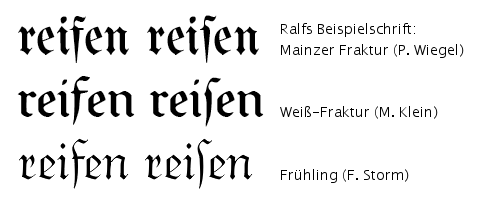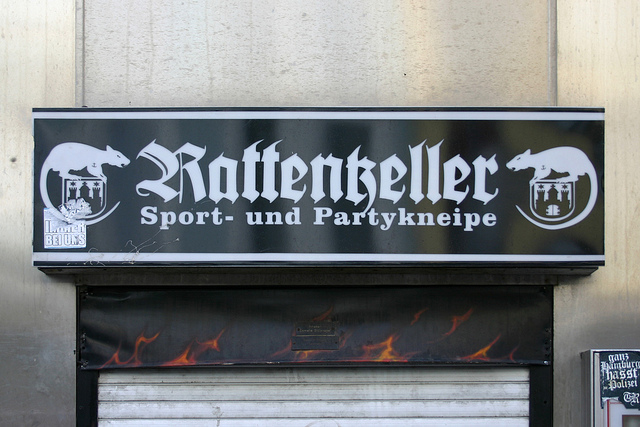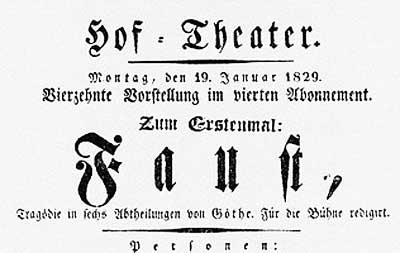
Neue Rechtschreibung?
Ich hab das Beispiel nicht gezielt »gesucht«. Ich hab in Erwartung einer Zwangsligatur nach Faust gesucht und das war das zweite Blatt, das mir unterkam. So sehen Titelblätter in den zurückliegenden Jahrhunderten nun mal aus – zu tausenden. Komm ich jetzt etwa in die Rolle, die alten Satzweisen zu verteidigen? :shock:
So sehen Titelblätter in den zurückliegenden Jahrhunderten nun mal aus
Stimmt. Goethes Faust erlebte übrigens am Braunschweiger Hoftheater seine Welturaufführung.
Die Kircheninschrift ist insgesamt so sehr homogenisiert, dass es der Lesbarkeit auch wieder schadet, m. E.
Das sehe ich genauso wie du.
Lesbarkeit war um 1509 natürlich nicht annähernd das Thema wie heute. Noch weniger lesbar sind die römischen Ziffern der Uhr.
Mir ist klar, dass wir 500 Jahre später nach anderen Maßstäben urteilen. Den Zweck erfüllte diese Schrift für die Menschen der damaligen Zeit. Trotzdem finde ich die gezeigten Arbeiten interessant, aber vielleicht habe ich die Bilder auch zu voreilig hochgeladen, da sie nicht unbedingt zum Thema passen.
Die Kriterien dieses Qualitätsanspruchs legt eben nicht irgendwer fest, sondern diejenigen, die über Schrift das nötige Wissen verfügen.
Dank für diesen Satz, knapper kann man es eigentlich kaum auf den Punkt bringen. Ich lege mich hier regelmäßig mit den Beauftragten für behinderte Studenten an wenn es um die Aufbereitung von Texten für Studenten mit Legasthenie geht. Ohne das nötige Fachwissen wird da eben einfach der größte Schrott etabliert. Und genau das ist es auch was mich immer wieder von der Idee abschreckt daß aktive Sprache ausschließlich von den Sprechenden geformt werden soll. Aber damit drehen wir uns im Kreis und es ist auch wieder nur meine persönliche Meinung.
Dank für diesen Satz, knapper kann man es eigentlich kaum auf den Punkt bringen. Ich lege mich hier regelmäßig mit den Beauftragten für behinderte Studenten an wenn es um die Aufbereitung von Texten für Studenten mit Legasthenie geht. Ohne das nötige Fachwissen wird da eben einfach der größte Schrott etabliert. …
Das würde voraussetzen, dass es nur eine Schriftanwendung gibt. Dem ist aber nicht so. Ein Text, der für Legastheniker aufbereitet wurde, wird vielleicht von Sehbehinderten schlecht erkannt, trotzdem müssen sich beide mit dem Text befassen. Der Qualitätsanspruch hängt also doch vom Adressaten ab und nicht ausschließlich von den Schriftkundigen.
Natürlich, aber unter welcher Voraussetzung denn? Die Studien die da gemacht werden benutzen dann Vorlagen in 12 pt Arial mit einfachem Zeilenabstand als Standard. Und vergleichen das mit z.B. Comic Sans. Welche andere Wahl haben denn die Probanden als Comic Sans oder Marker Felt unter diesen Umständen als besser Lesbar zu identifizieren?
Ein falscher Ansatz kann nur zu falschen Ergebnissen führen, da geb ich dir recht. Ich finde nur Erwin Krumps verallgemeinernde Aussage „Die Kriterien dieses Qualitätsanspruchs legt eben nicht irgendwer fest, sondern diejenigen, die über Schrift das nötige Wissen verfügen.“ nicht richtig, weil der Qualitätsanspruch bei unterschiedlichen Adressaten so unterschiedlich ist, dass es keine Lösung für alle gibt. Auch, weil die Schriftkundigen gar nicht alle alle Ansprüche kennen können.
Ich finde nur Erwin Krumps verallgemeinernde Aussage „Die Kriterien dieses Qualitätsanspruchs legt eben nicht irgendwer fest, sondern diejenigen, die über Schrift das nötige Wissen verfügen.“ nicht richtig, weil der Qualitätsanspruch bei unterschiedlichen Adressaten so unterschiedlich ist, dass es keine Lösung für alle gibt. Auch, weil die Schriftkundigen gar nicht alle alle Ansprüche kennen können.
Aber der Satz „die über Schrift das nötige Wissen verfügen“ – beinhaltet ja genau das, was du nun ansprichst, dass sich der Fachmann(frau) auch mit der Zielgruppe (mit den jeweiligen Adressaten, wie du schreibst) entsprechend auseinandergesetzt hat. Dass die Bedürfnisse derjenigen, für die dieses Produkt hergestellt werden soll und die es dann benutzen oder benötigen, berücksichtigt wird, spielt in der Entscheidungsfindung der Umsetzung genau die entsprechende Rolle.
Was ist daran verallgemeinernd?
Man sehe sich nur »Entréen« an, um zu sehen, was für ein Schriftsetzer das verzapft hat.
Nur eine Anmerkung aus der Bleisetzerei zur Ehrenrettung des Kollegen: Ich hatte in Blei noch nie eine Fraktur mit Akzenten in der Hand. Eigentlich setzt man Fremdwörter in einem Fraktur-Text aus Antiqua, aber diese Lösung ist für 1829 auch gut.
Eigentlich setzt man Fremdwörter in einem Fraktur-Text aus Antiqua …
Richtig. Alternativ kann man auch zur Feile greifen und einen Akzent über das Fraktur-e basteln. Aber der Antiqua-Buchstabe im Fraktur-Wort ist m. E. die schlechteste aller denkbaren Möglichkeiten, da wäre es sogar noch besser, den Akzent ganz wegzulassen.
… den Setzer möchte ich sehen, der ein Tertia- oder Text-e anfeilt und dann einen Akzent - woher eigentlich nimmt?
Genau.
Wie ich gerade auf der Ligafaktur-Seite sehe, hat man neben Wach-s-tube und Ver-s-endung noch weitere schlagkräftige Wortbeispiele aufgetan, die das Scheitern der Rechtschreibreform belegen und Adelung’sche Schreibung und am liebsten auch das ſ zurückholen sollten:
• Mes­sende — der Messende oder das Mess-Ende (!?)
• Passende — das Passende oder das Pass-Ende
Ah, ja.